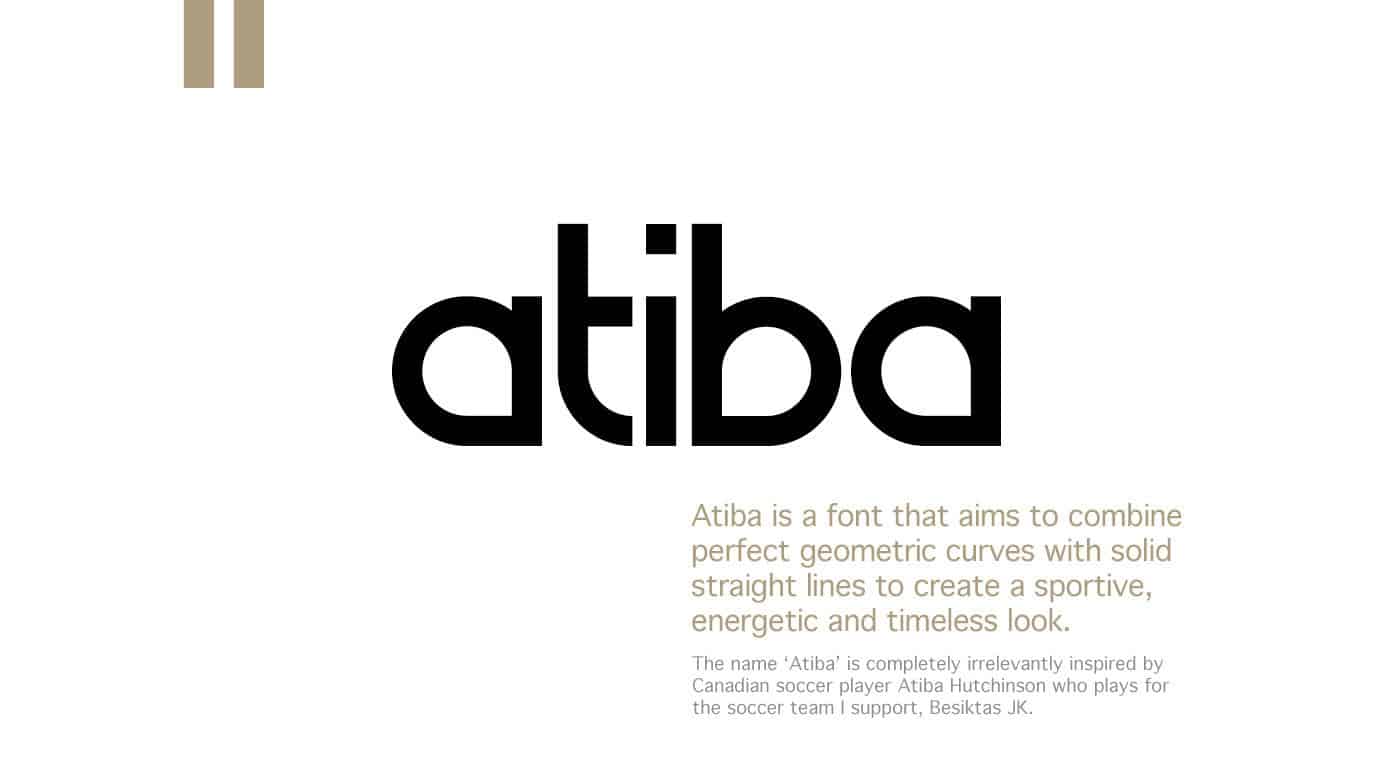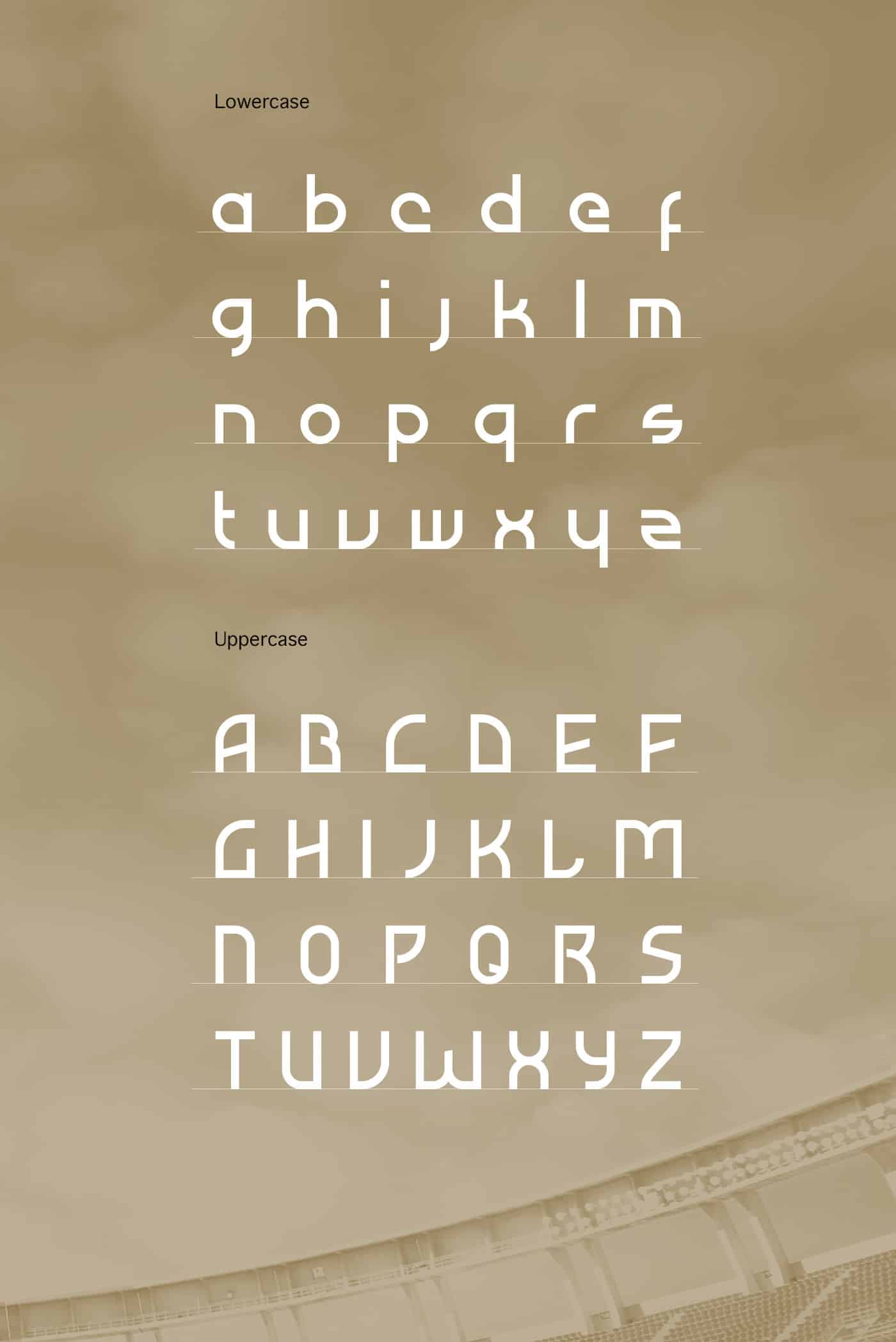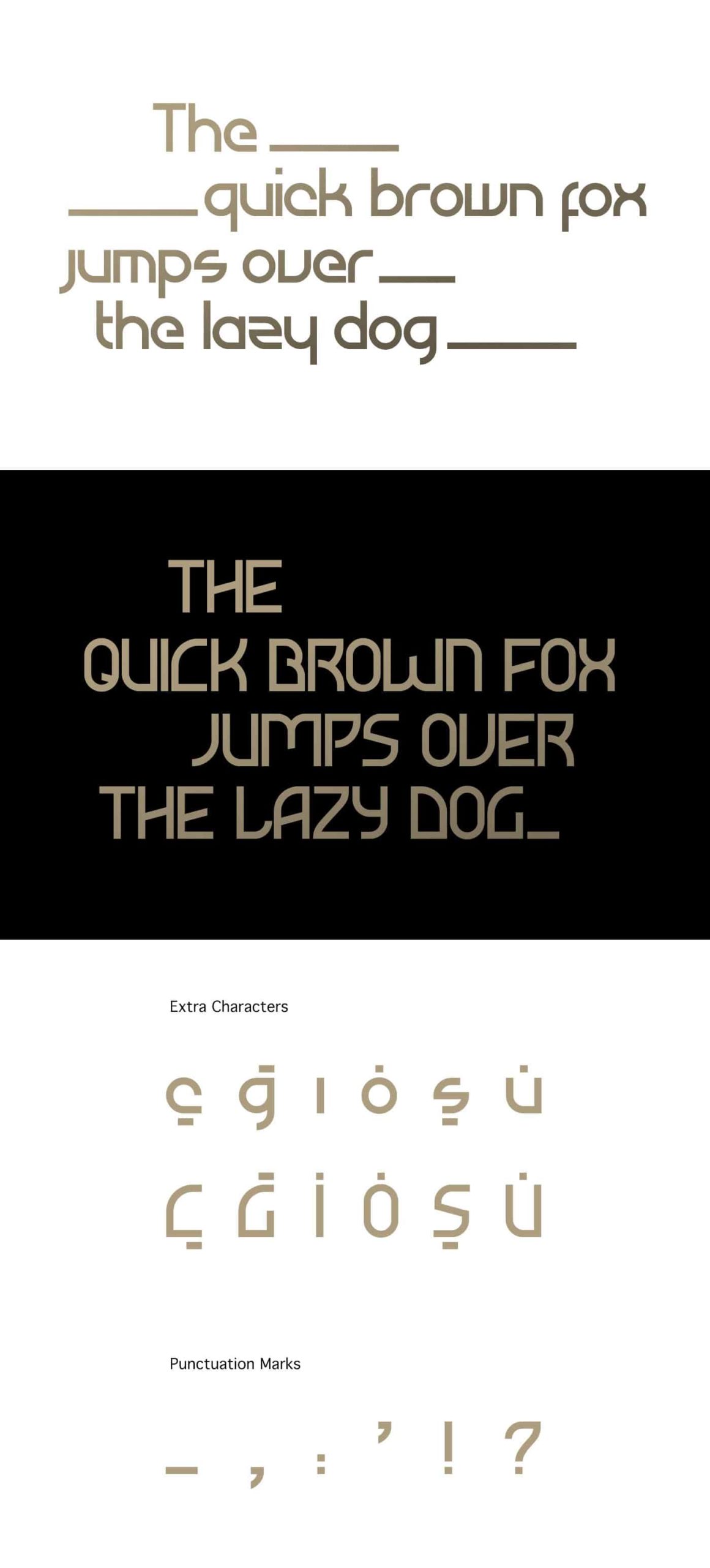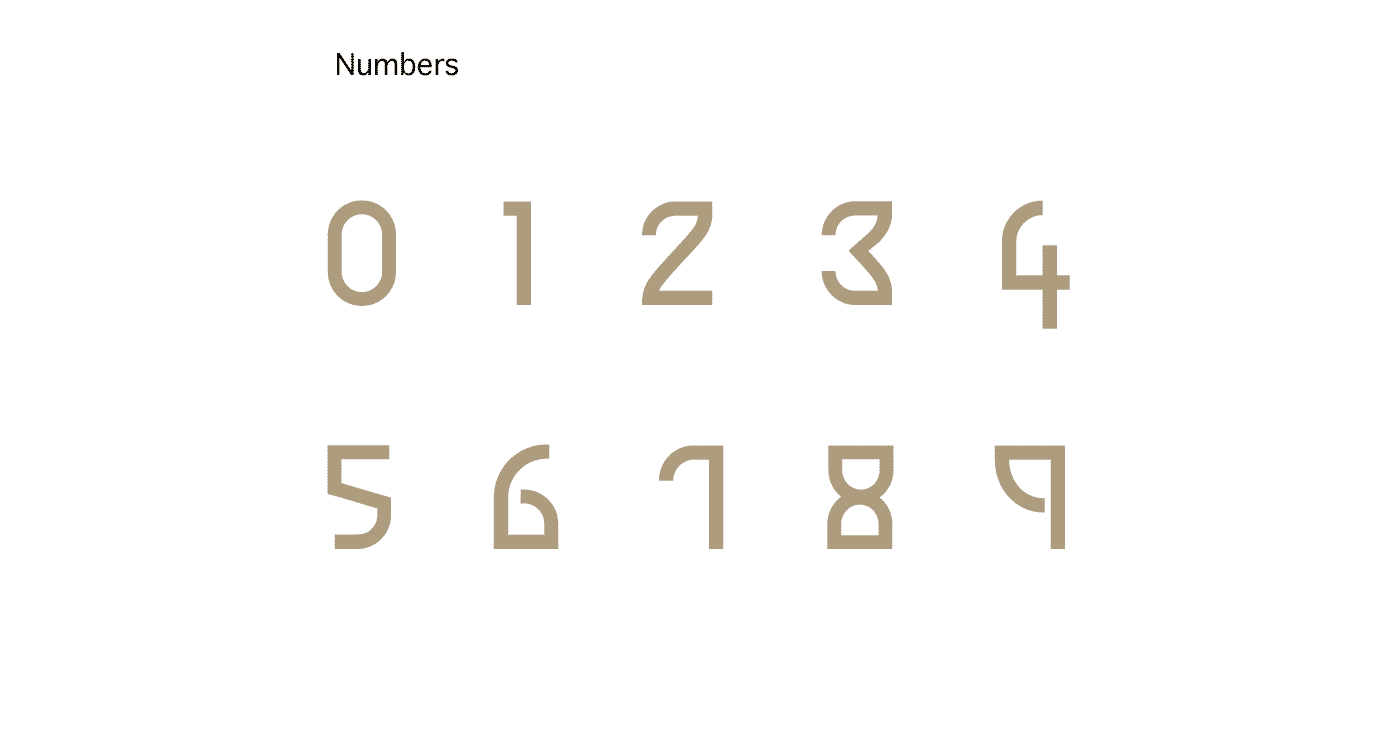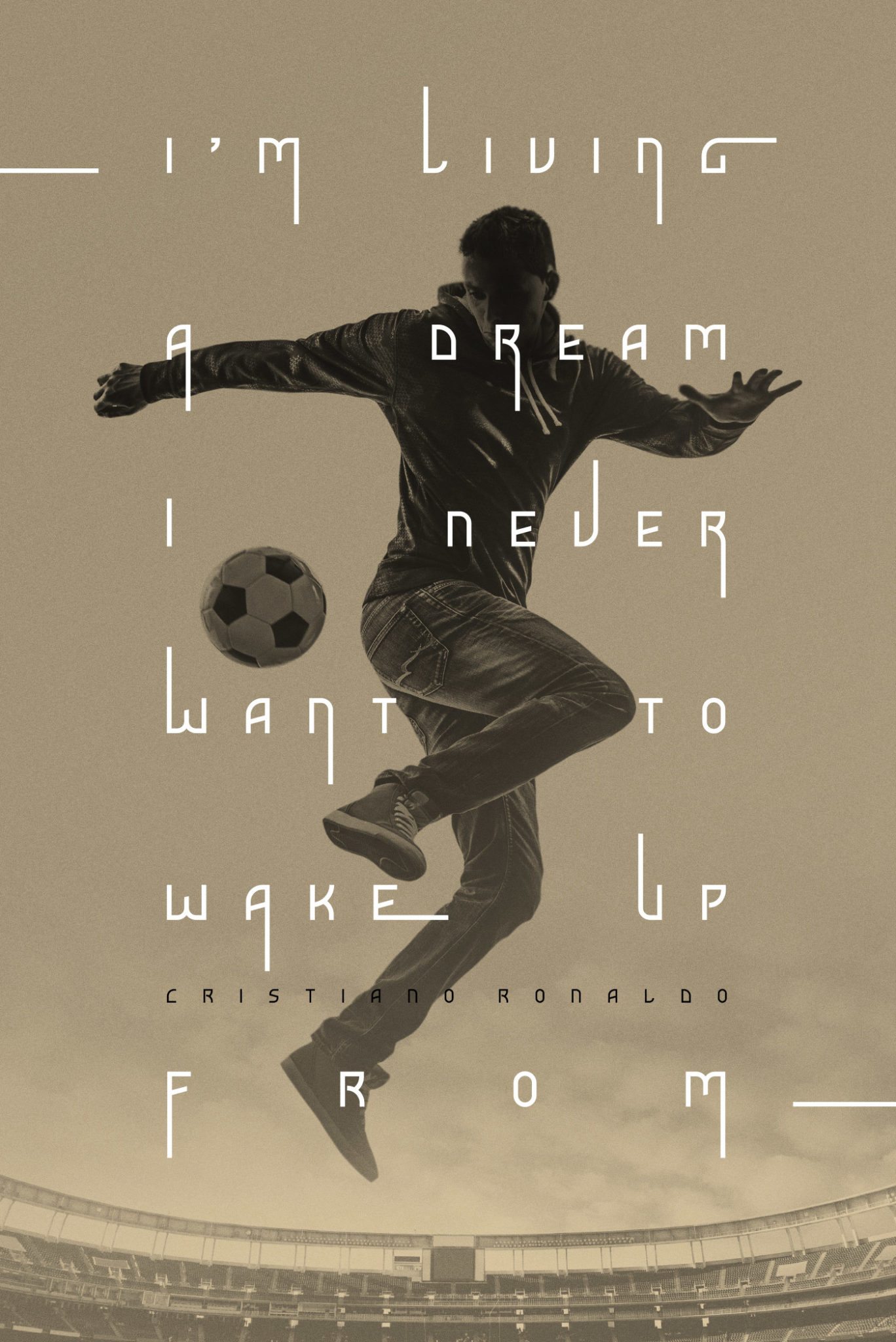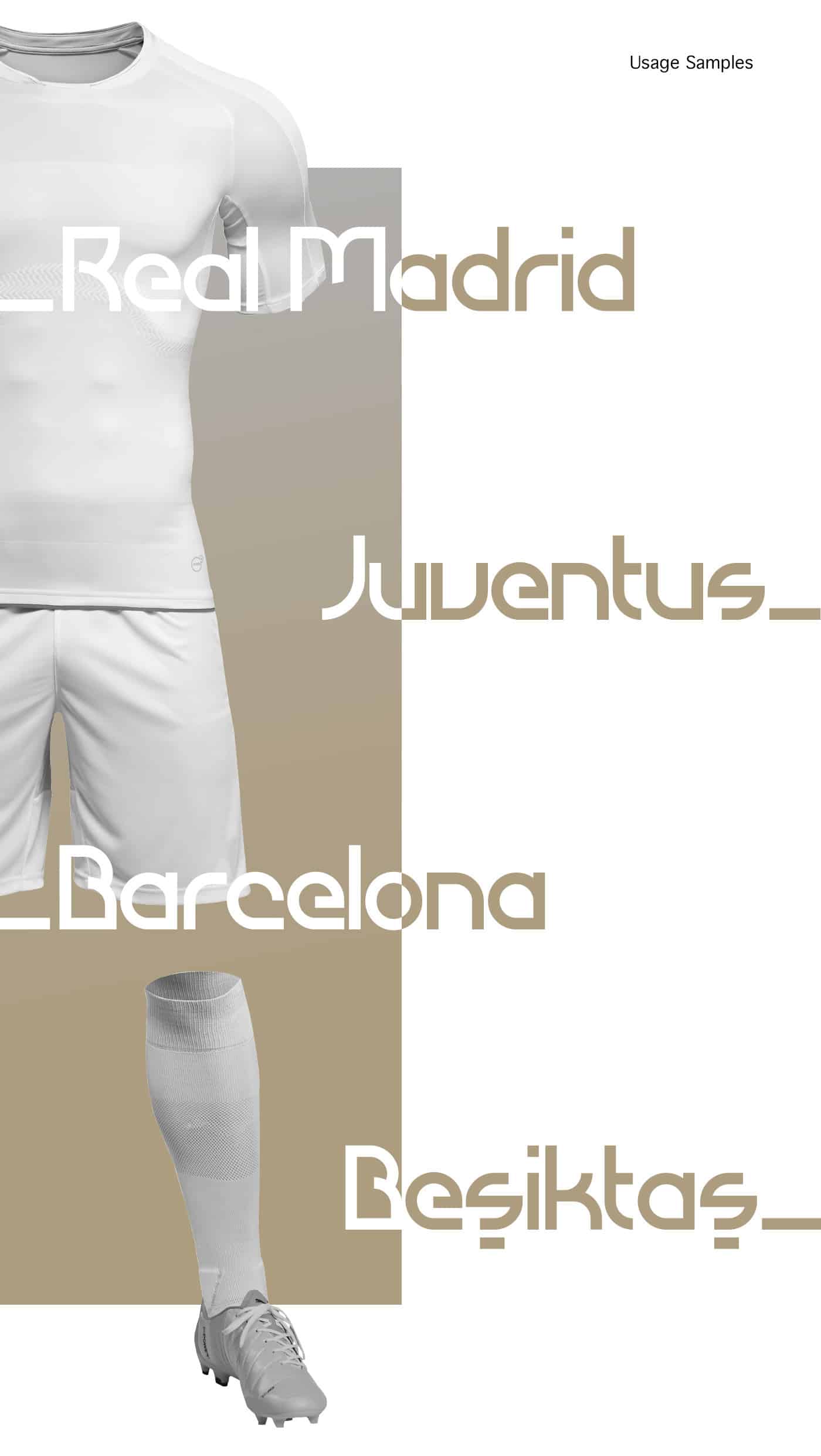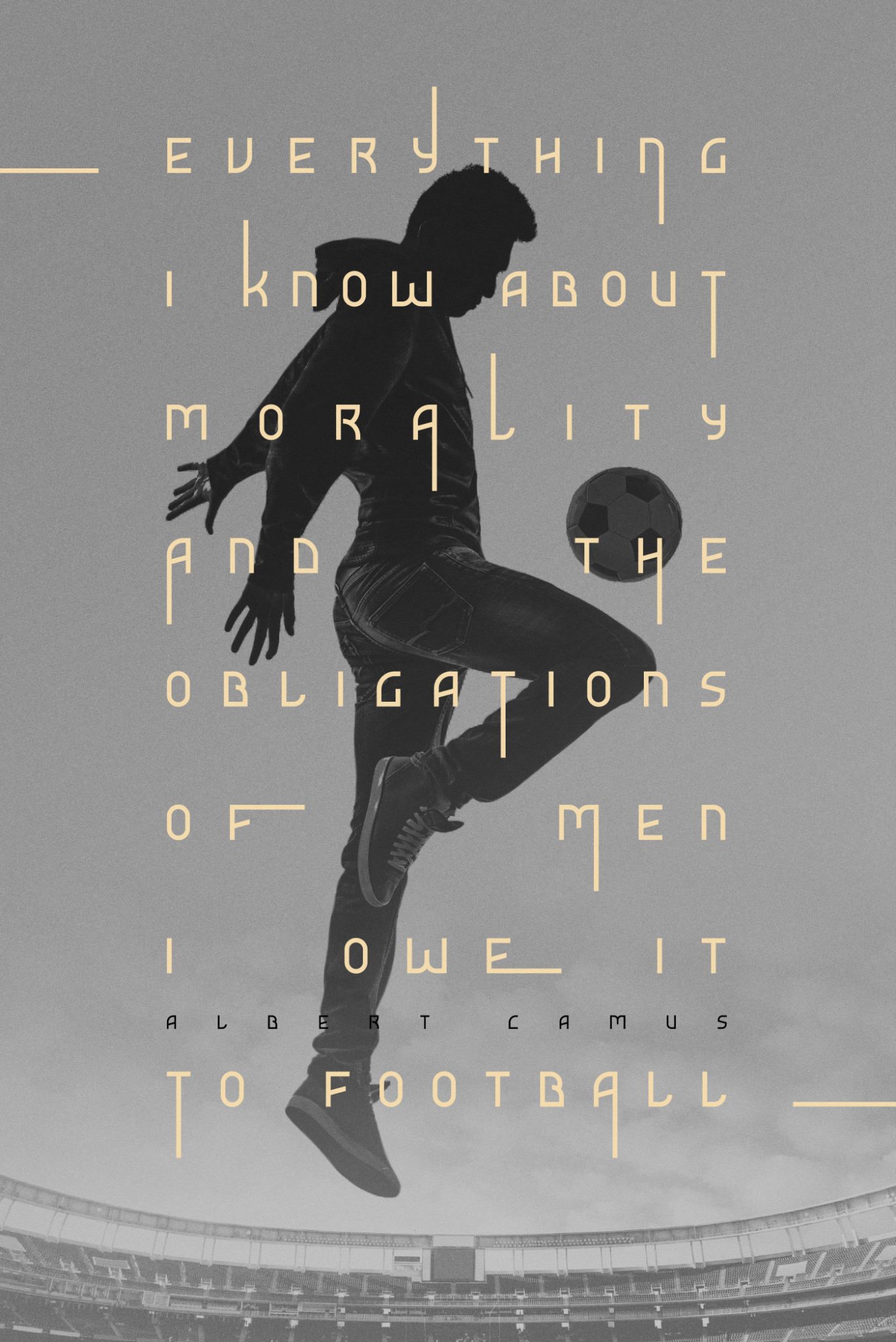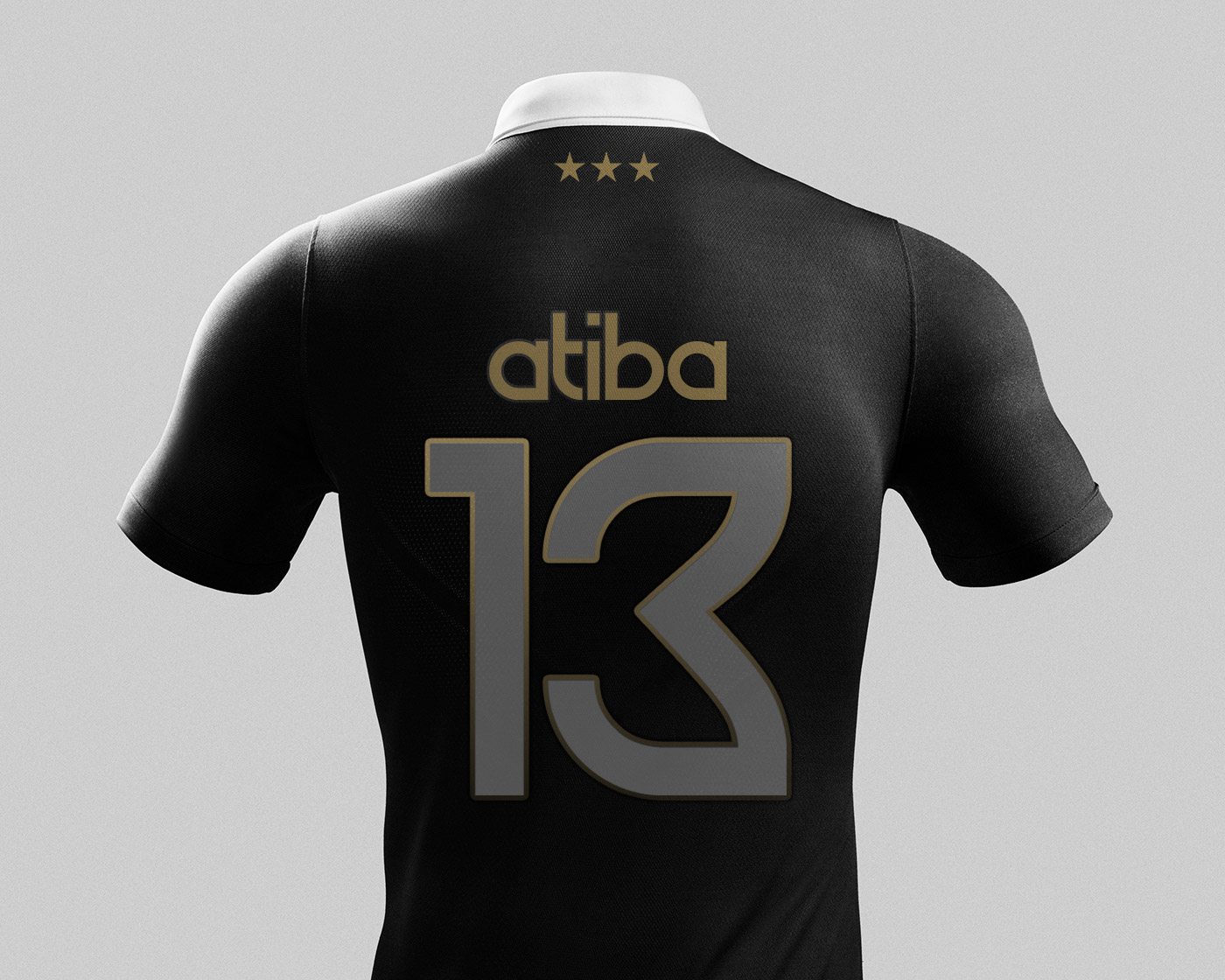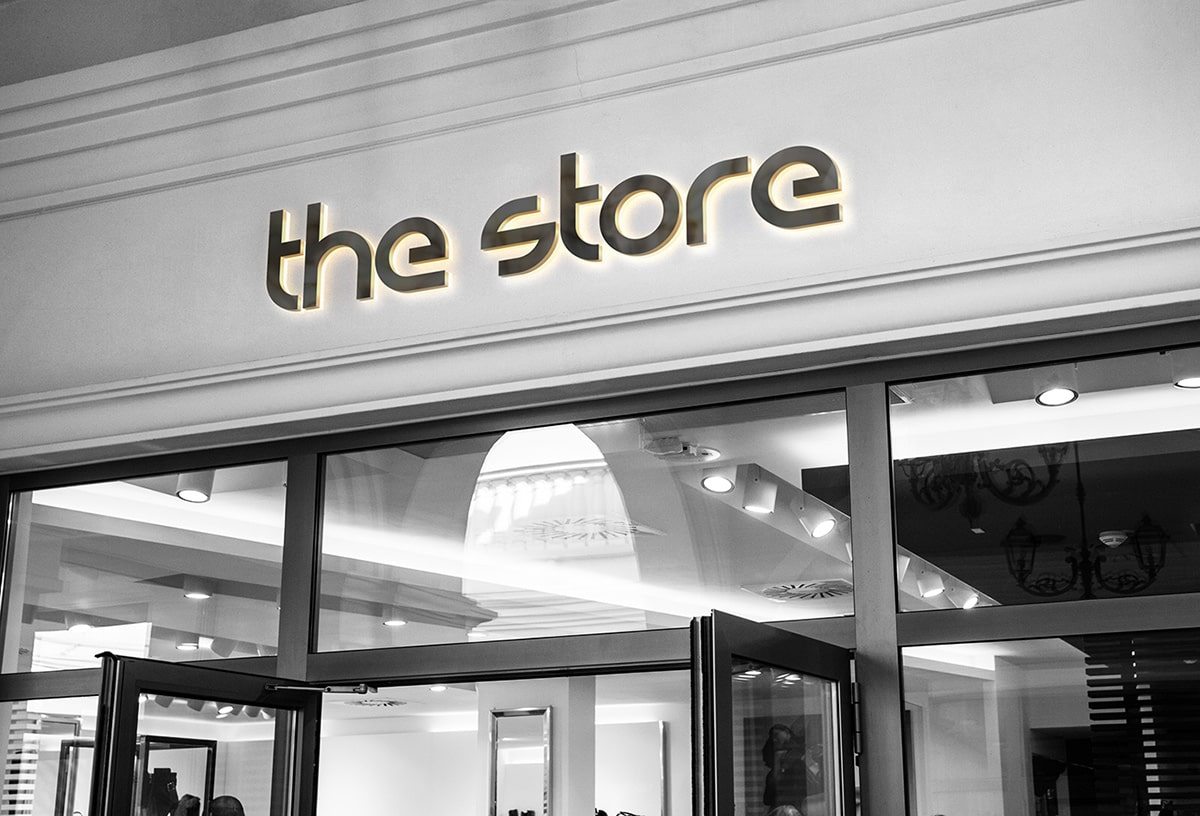
font del giorno Atiba
Il font che vi presentiamo oggi é: Atiba
Atiba  è il nuovo font realizzato da Ozan Karakoc
il font atiba e er chi ama combinare linee geometriche curve a incroci netti ottenendo un font pieno di energia e molto sportivo